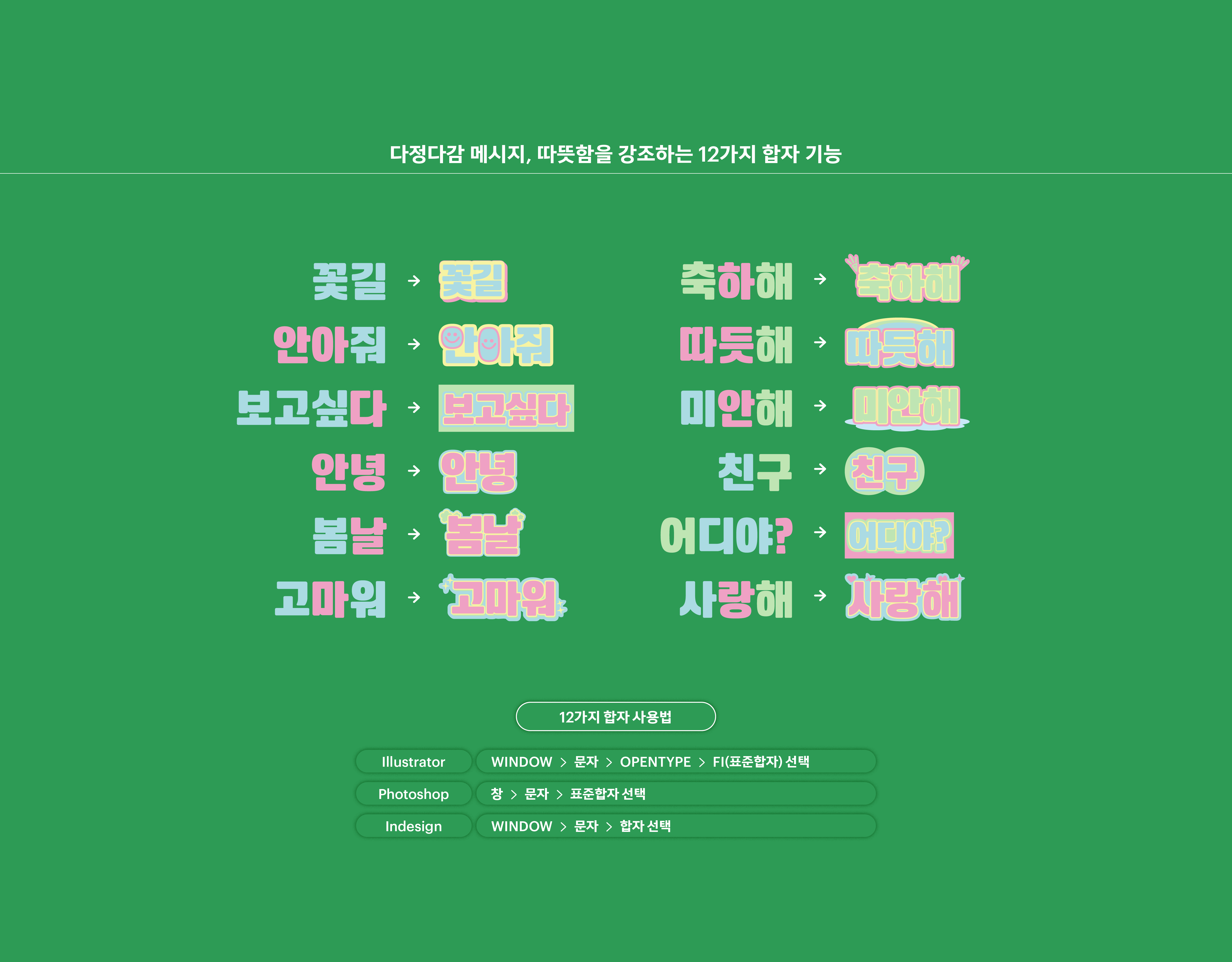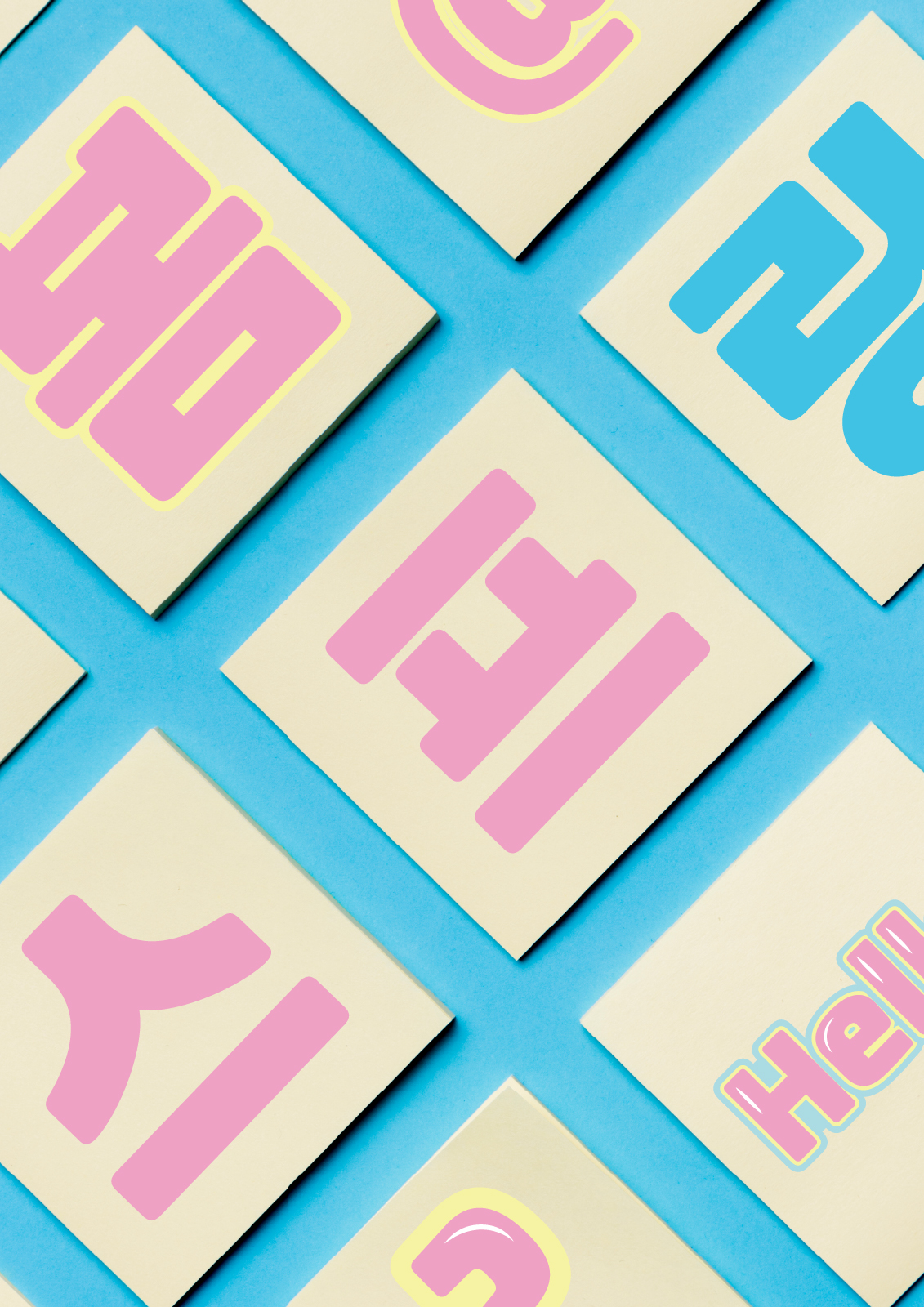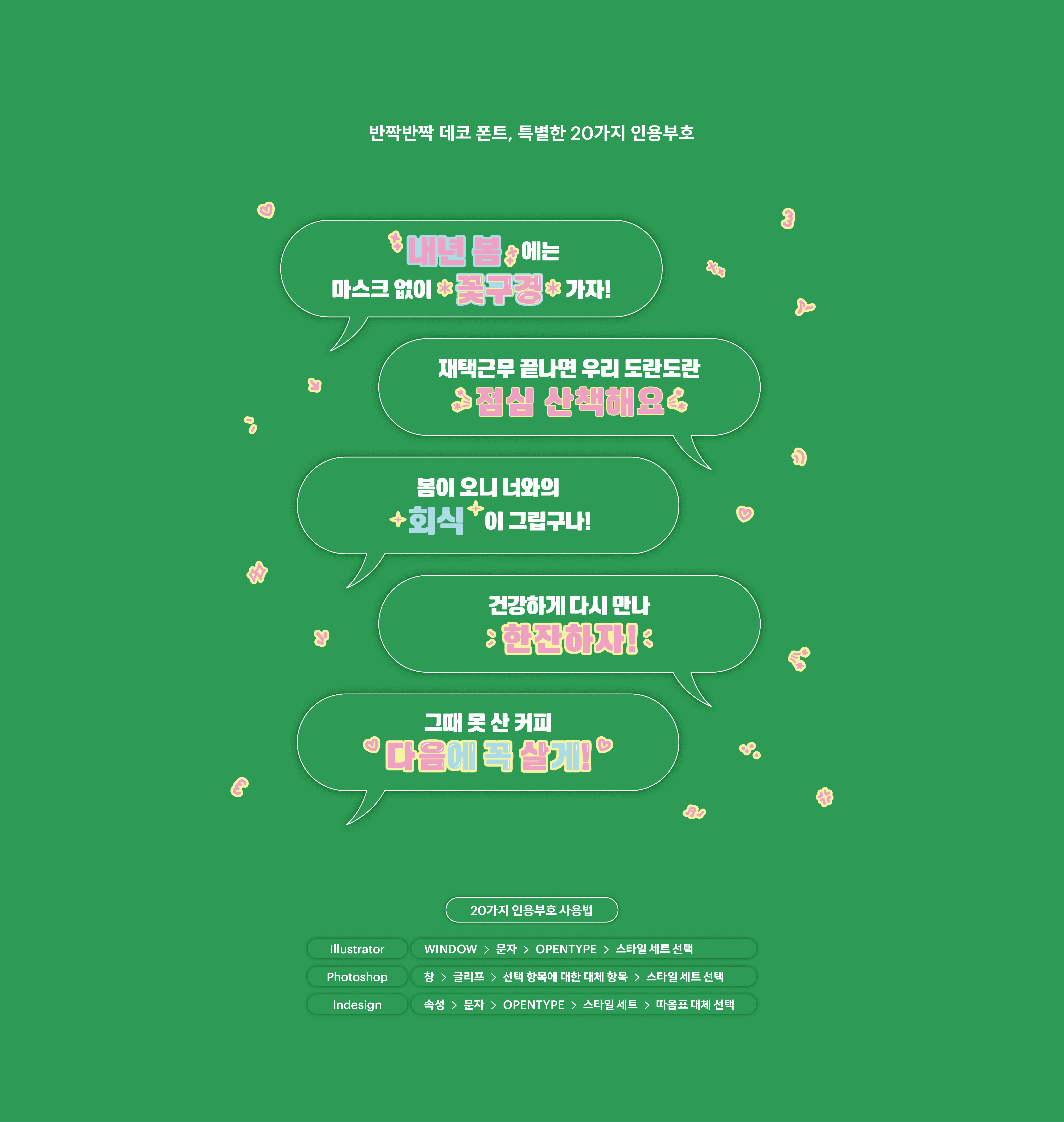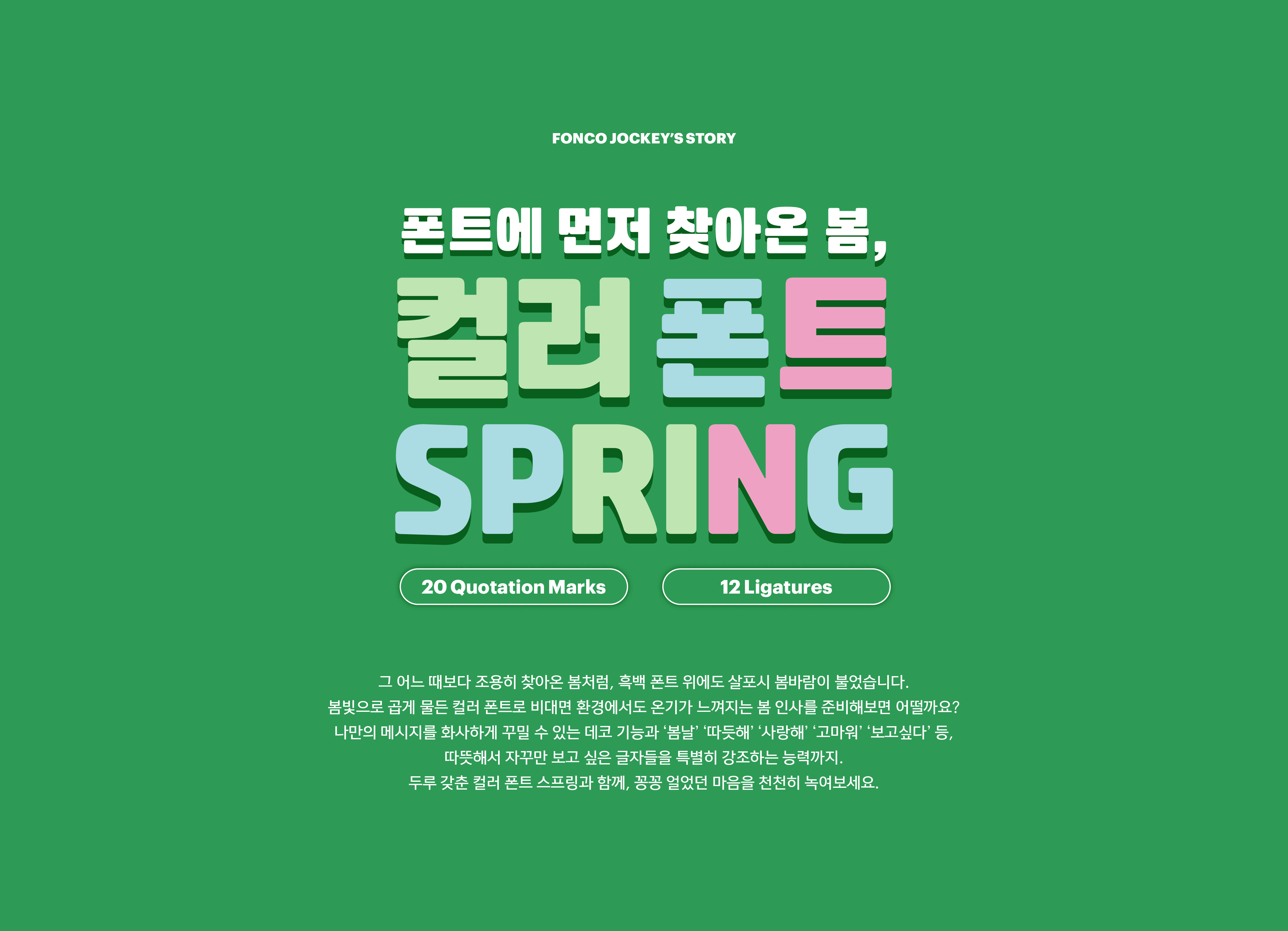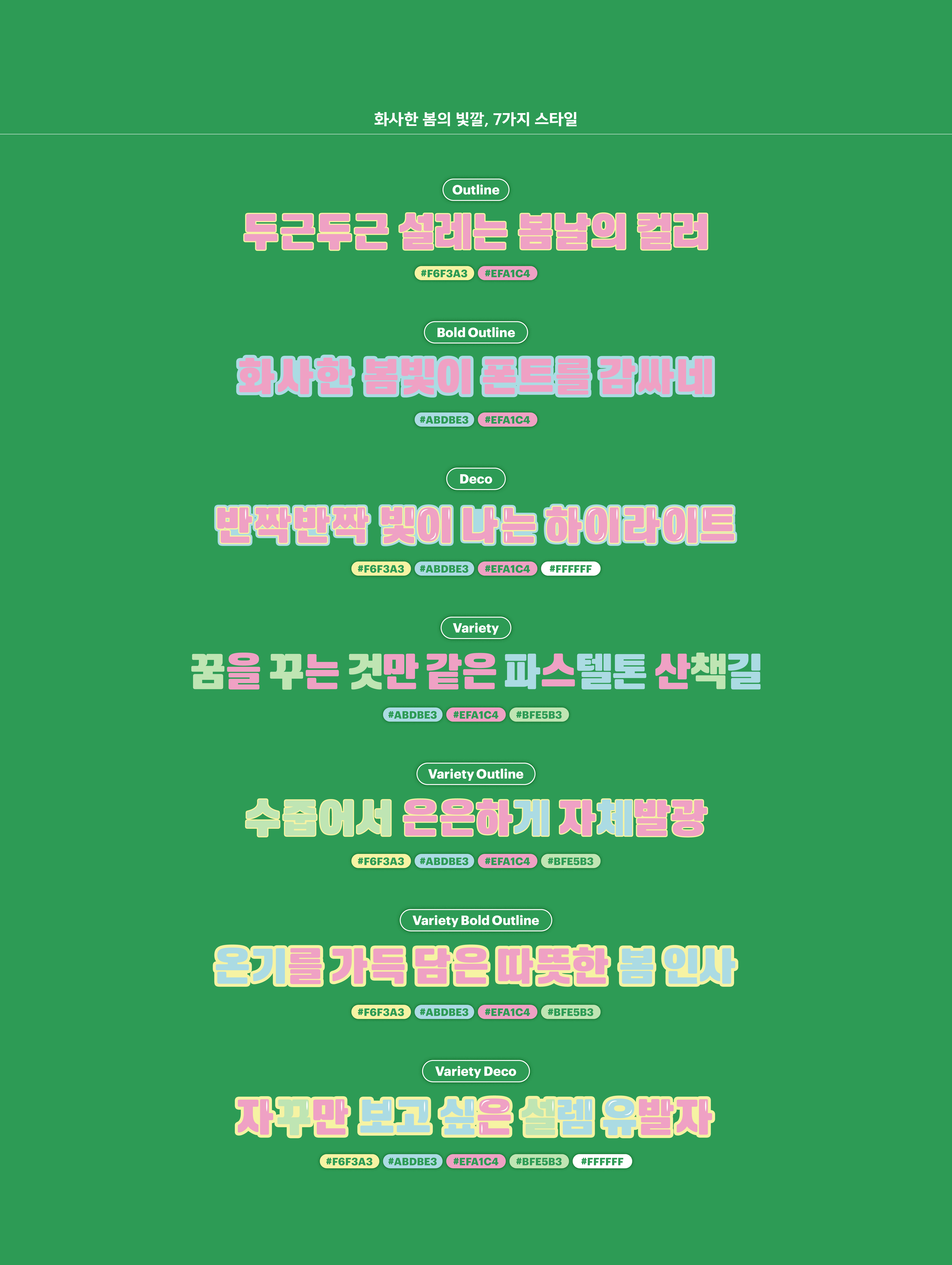
Yoon 스프링 Color
그 어느 때보다 조용히 찾아온 봄처럼, 흑백 폰트 위에도 살포시 봄바람이 불었습니다. 봄빛으로 곱게 물든 컬러 폰트로 비대면 환경에서도 온기가 느껴지는 봄 인사를 준비해보면 어떨까요? 나만의 메시지를 화사하게 꾸밀 수 있는 데코 기능과 '봄날' '따듯해' '사랑해' '고마워' '보고싶다' 등, 따뜻해서 자꾸만 보고 싶은 글자들을 특별히 강조하는 능력까지. 두루 갖춘 컬러 폰트 스프링과 함께, 꽁꽁 얼었던 마음을 천천히 녹여보세요.